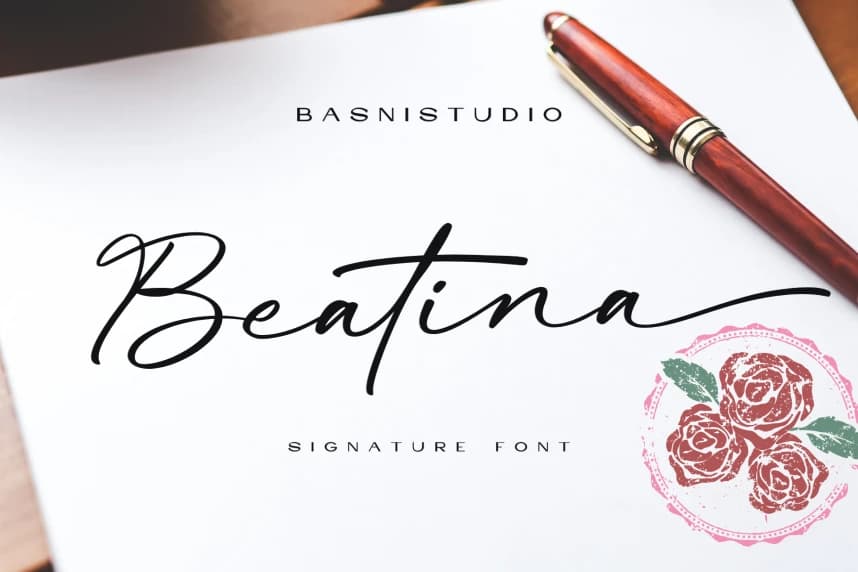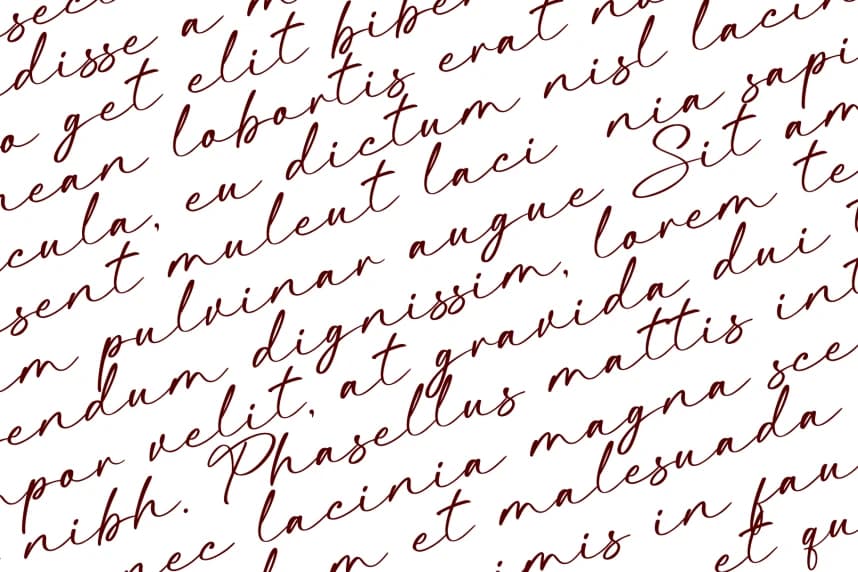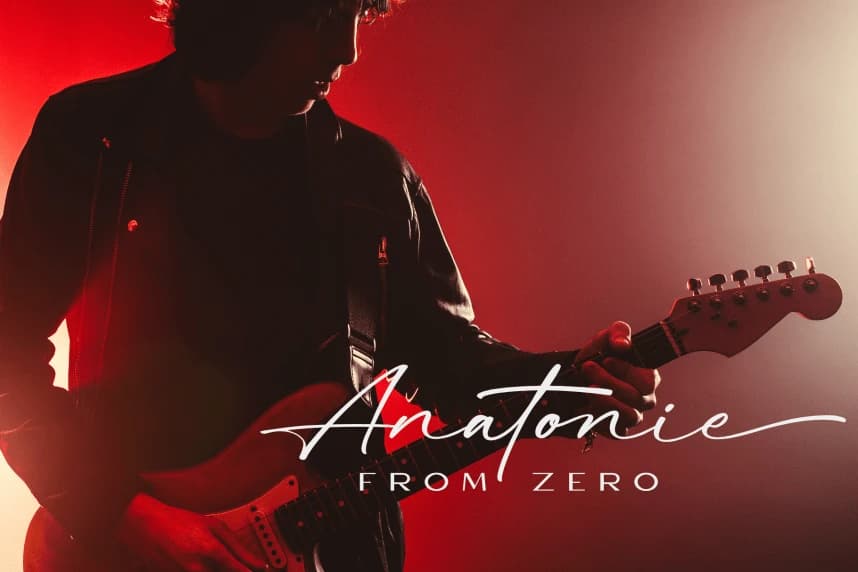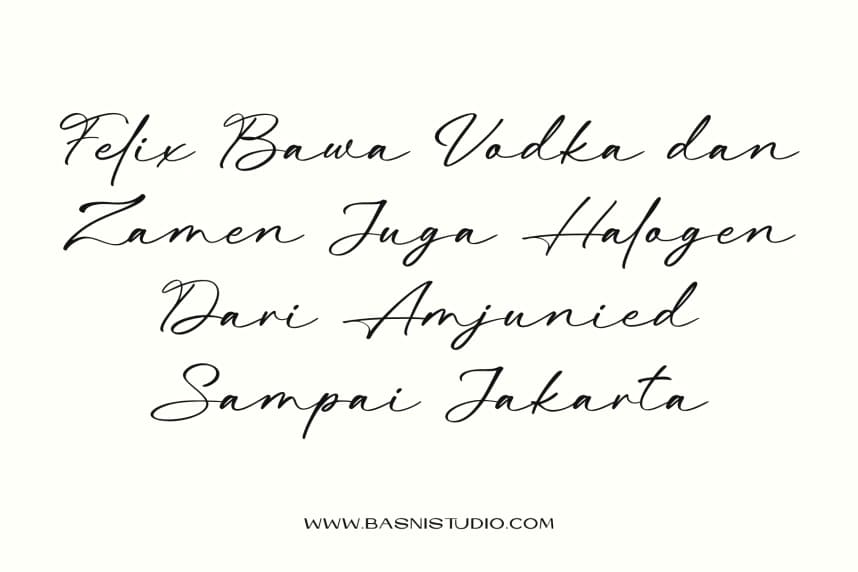
Beatina – İmza Yazı Tipi
Beatina – Signature Font otantik fırça ile tasarlanmış, doğal & rahat dokunuş için; markalaşmadan sosyal medyaya kadar, davetiyeler ve ambalajlar dahil her şey.
Beatina – Signature Font gerçek fırça ile tasarlanmış, doğal ve rahat bir dokunuş sunar; markalaşma ve sosyal medyadan davetiyelere ve ambalajlara kadar her şey için.